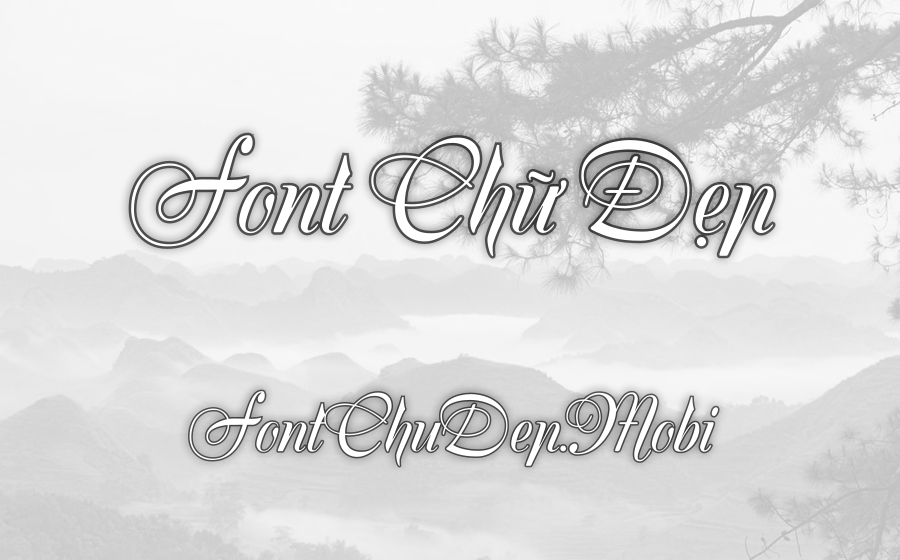
Font UTM Silk Script Việt Hóa
UTM Silk Script
UTM Silk Script là một trong những font chữ viết tay đầy cuốn hút mà mình đã có cơ hội trải nghiệm. Đến từ bộ sưu tập font UTM, font này gây ấn tượng bởi những đường nét mềm mại và uyển chuyển, mang lại sự tinh tế và giàu cảm xúc nghệ thuật cho bất kỳ thiết kế nào.
Một trong những điểm khiến mình cực kỳ yêu thích UTM Silk Script chính là sự hòa quyện tinh tế giữa phong cách cổ điển và hiện đại. Điều này làm cho font chữ trở thành lựa chọn lý tưởng cho nhiều dự án khác nhau như thiệp mời, tiêu đề sách, poster hay bất kỳ ấn phẩm nghệ thuật nào. Đặc biệt, font này đã được Thiên Minh Việt hóa kỹ lưỡng, hỗ trợ đầy đủ các dấu và ký tự tiếng Việt. Điều này chắc chắn mang lại sự thuận tiện và trải nghiệm hoàn thiện cho người sử dụng trong nước. Bên cạnh đó, khả năng hỗ trợ nhiều ngôn ngữ khác cũng giúp UTM Silk Script dễ dàng ứng dụng trong các dự án mang tính quốc tế.